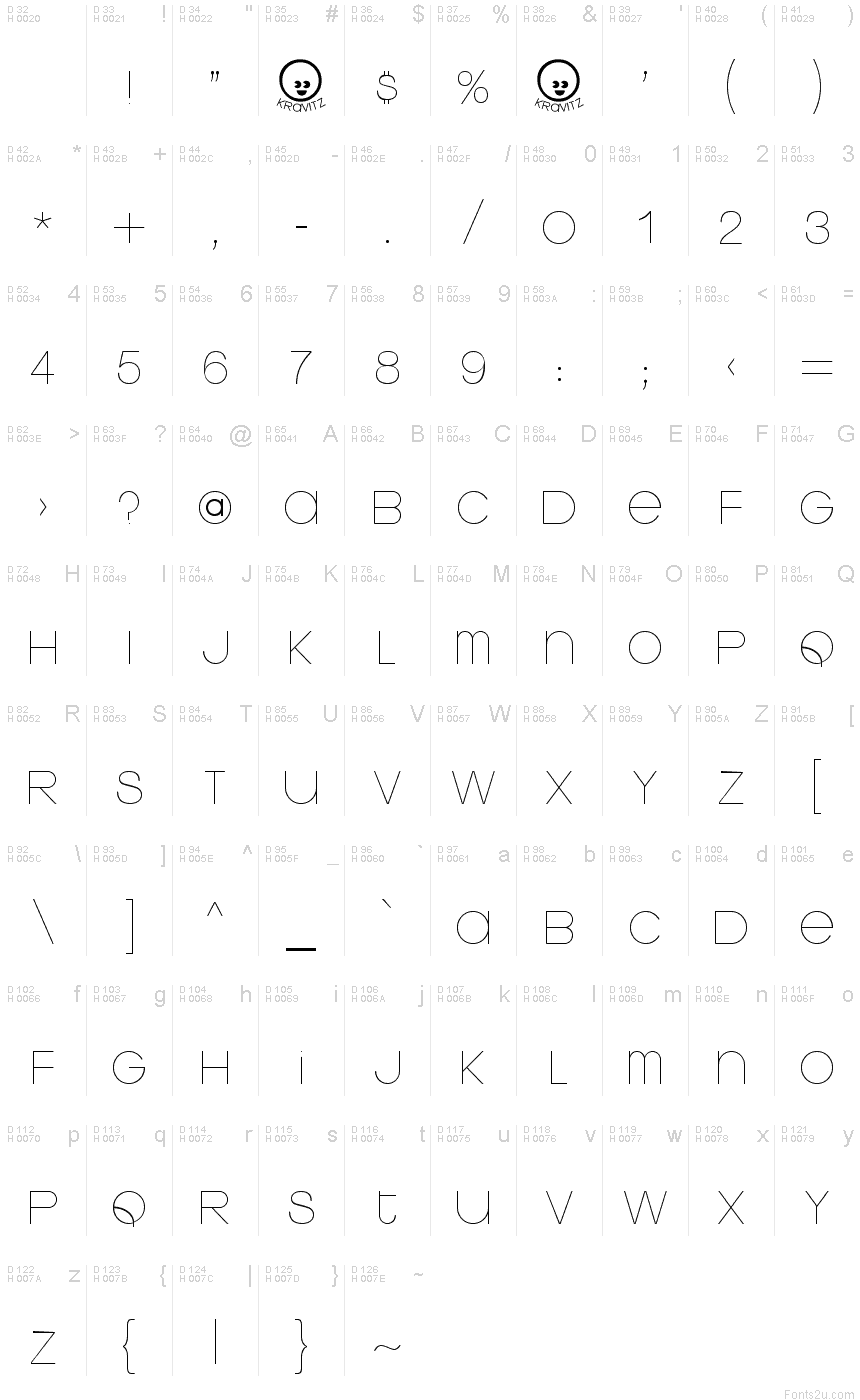
Kravitz od Font'a'licious Fonts to wąski, bezszeryfowy krój pisma o równomiernej kresce i zaokrąglonej geometrii. Litery sprawiają wrażenie lekkich i liniowych; proste linie przechodzą w łagodne łuki, zachowując oszczędny, ale nieprzeładowany charakter. Otwarte kształty nadają każdemu słowu spokojny, wyważony rytm.
Kravitz świetnie sprawdzi się w projektach dla marek modowych, okładkach, plakatach oraz minimalistycznych opakowaniach, gdzie wydłużone formy przyciągają wzrok bez zbędnych dekoracji. Doskonale pasuje również do szkiców logo, oznakowań i menu, które wymagają wyrafinowanego, surowego wyrazu.